한문 초서는 한자의 필기체로, 빠르게 글씨를 쓸 수 있도록 단순화된 형태예요. 하지만 획이 생략되거나 변형되는 경우가 많아 판독이 쉽지 않아요. 초서를 정확히 읽으려면 기초적인 서체 구조를 이해하고 자주 쓰이는 생략 패턴을 익히는 것이 중요해요.
내가 생각했을 때 초서를 해독하는 능력은 단순히 글자를 읽는 것이 아니라, 당시 문맥과 필체의 흐름을 파악하는 것이 핵심이에요. 초서 판독의 기본 원칙과 실전 노하우를 익히면 역사적인 문서나 고문서를 해독하는 능력이 크게 향상될 거예요.
📖 초서의 기원과 특징
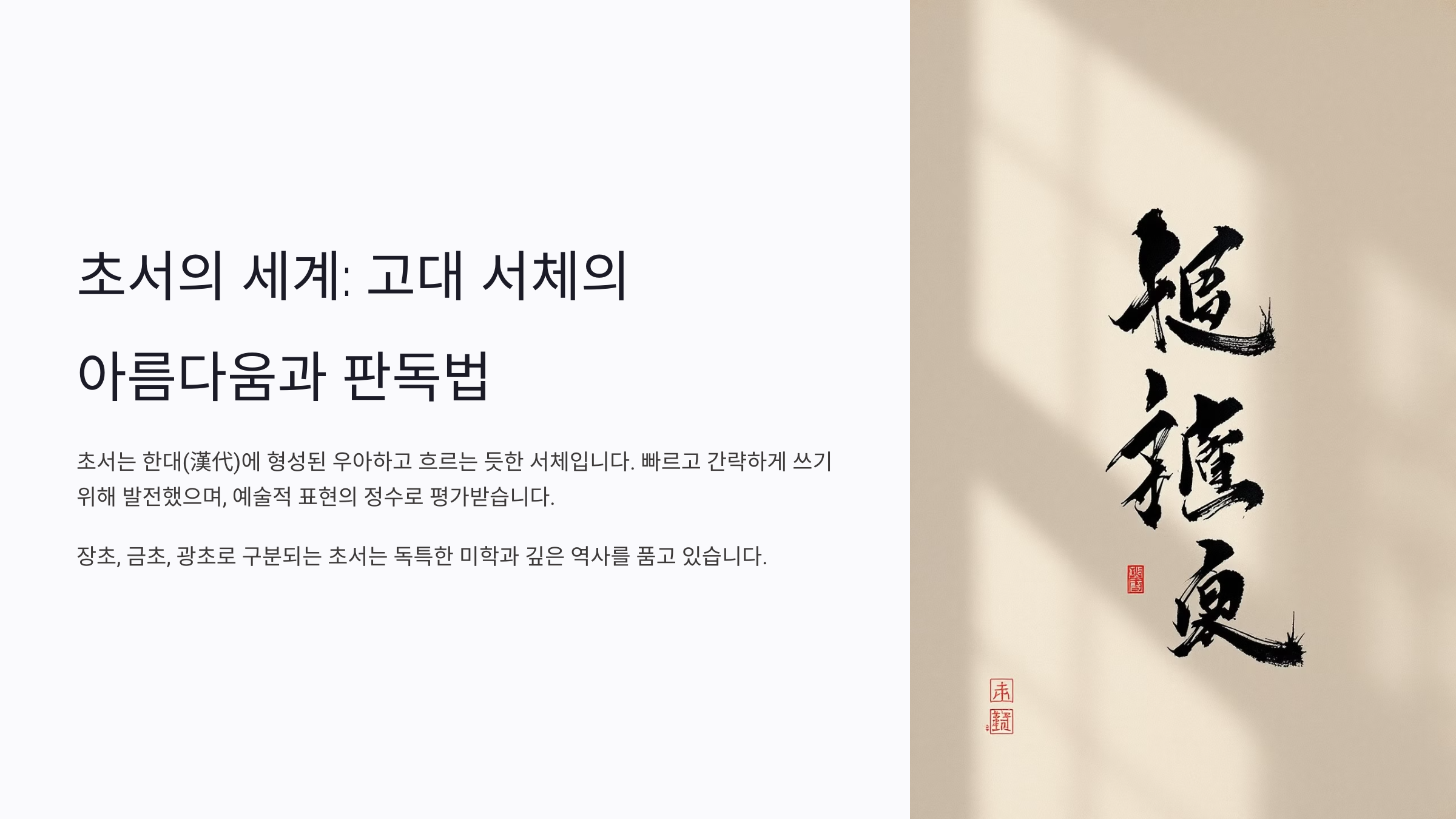
초서는 한자의 필기체로, 한대(漢代)부터 발전하기 시작했어요. 한자의 기존 획을 단순화하고 이어 쓰면서 더욱 빠르게 기록할 수 있도록 만들어졌어요. 당시 관료나 학자들이 문서를 신속하게 작성할 필요가 있었기 때문에 초서가 널리 사용되었죠.
초서는 크게 장초(章草)와 금초(今草), 광초(狂草)로 나뉘어요. 장초는 전서나 예서의 특징이 남아 비교적 읽기 쉬운 편이에요. 반면, 금초와 광초는 획이 더욱 과감하게 생략되고 연결되어 난해한 경우가 많아요.
초서가 가장 발달한 시기는 당대(唐代)로, 손과 팔의 자연스러운 움직임을 강조한 필법이 정립되었어요. 대표적인 초서 대가로는 장욱(張旭), 회소(懷素) 같은 인물들이 있어요.
📝 초서 유형 비교표
초서 유형 특징 난이도 대표 서예가 장초(章草) 예서에 가까운 초서, 상대적으로 쉽게 판독 가능 ★☆☆☆☆ 서승(徐僧), 두우(杜佑) 금초(今草) 획이 연결되고 약간의 생략이 있는 초서 ★★★☆☆ 장욱(張旭), 손과(孫過) 광초(狂草) 획의 생략과 변형이 극대화된 초서 ★★★★★ 회소(懷素), 장욱(張旭) 초서의 유형별 특징을 이해하면 문서의 난이도를 예측하고 판독에 접근하기 쉬워요. 특히 장초부터 시작해 점차 금초, 광초로 넘어가는 연습이 중요해요.
🖋 초서의 기본 구조와 서법
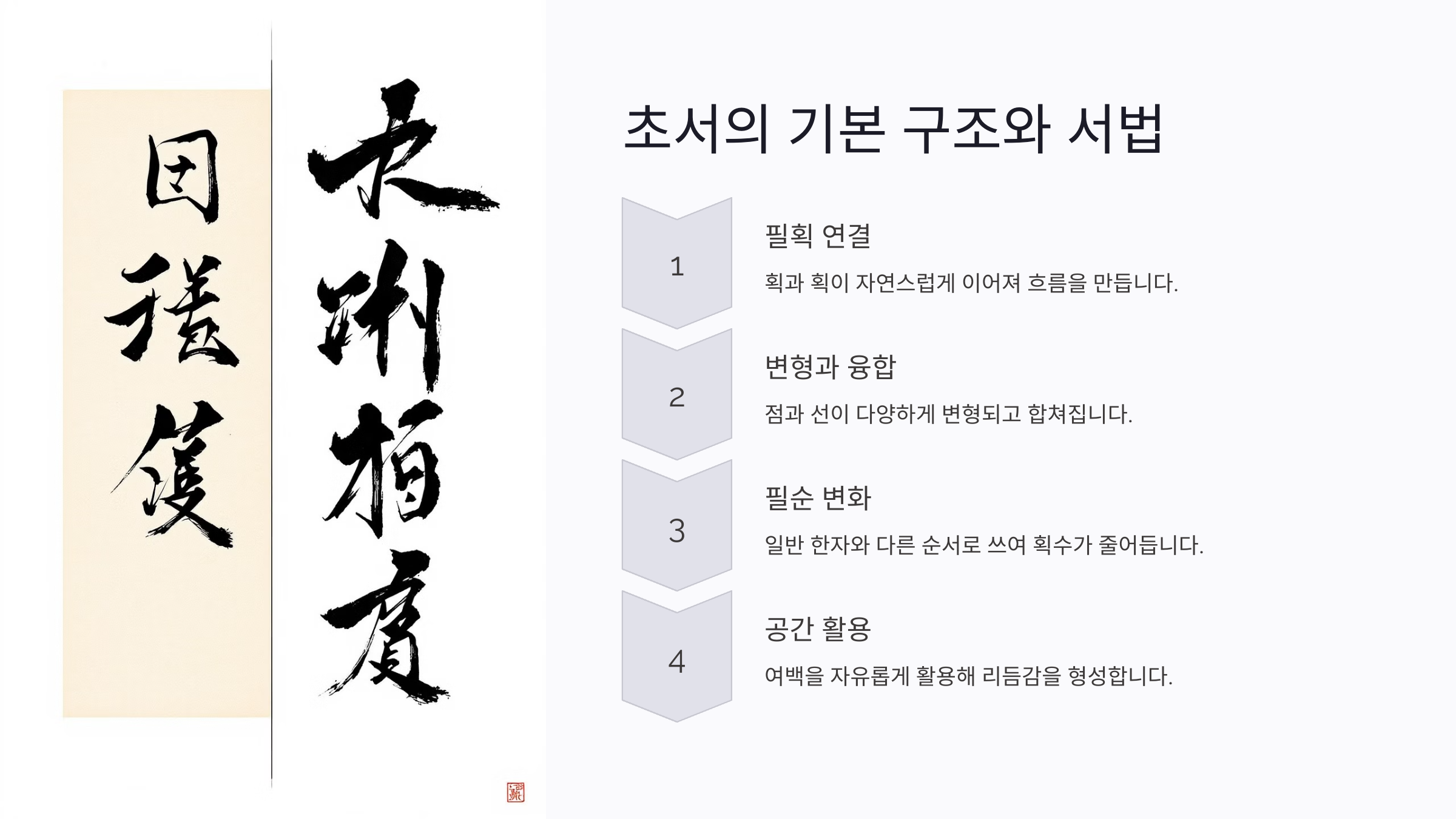
초서는 기본적으로 기존 한자의 획을 간략하게 줄이거나 이어 쓰는 방식으로 구성돼요. 글자의 균형을 유지하면서도 빠른 필기가 가능하도록 변형되었기 때문에 초서를 읽기 위해서는 이러한 변형 원리를 이해하는 것이 중요해요.
초서의 기본 원리는 획 생략(省筆), 획 연결(連筆), 획 변화(變筆)로 나뉘어요. 이를 통해 기존 한자의 형태가 완전히 달라질 수 있어요. 예를 들어, '永(영)'자는 초서에서 단순한 곡선으로 변형될 수 있고, '書(서)'자는 여러 획이 한 붓으로 연결되기도 해요.
초서를 작성할 때 중요한 요소는 ‘서법(書法)’이에요. 초서는 단순히 글씨를 빨리 쓰는 것이 아니라, 특정한 필법과 흐름을 유지하는 것이 핵심이에요. 필획의 방향, 필압, 속도 등에 따라 글자의 분위기가 완전히 달라질 수 있어요.
✍ 초서 변형 원리
변형 원리 설명 예시 획 생략 (省筆) 글자의 일부 획을 생략하여 간결화 書 → 弢 획 연결 (連筆) 여러 획을 한 번에 이어 써서 필기 속도 향상 水 → 氵 획 변화 (變筆) 획의 형태를 변형하여 새로운 글씨체로 발전 馬 → 屮 초서를 판독하려면 이런 변형 패턴을 익혀야 해요. 특히 ‘획 생략’과 ‘획 연결’이 많이 적용된 글자는 난이도가 높기 때문에 초서 대가들의 필적을 참고하는 것도 좋은 방법이에요.
🔍 초서 판독을 위한 핵심 규칙
초서를 정확하게 판독하려면 몇 가지 핵심 규칙을 이해하는 것이 중요해요. 초서의 특징상 획이 연결되거나 생략되는 경우가 많아, 문맥을 고려하며 해석해야 해요. 단순히 글자 하나하나를 읽는 것이 아니라, 문장 전체의 흐름을 파악하는 것이 핵심이에요.
초서를 판독할 때 가장 먼저 해야 할 일은 '획의 패턴'을 파악하는 것이에요. 초서는 필기 속도를 높이기 위해 획을 줄이거나 이어 쓰는 특징이 있기 때문에, 특정 패턴이 반복되는 경우가 많아요. 초서에서 자주 변형되는 글자들을 익히면 판독이 훨씬 쉬워져요.
또한, 필기 습관에 따라 동일한 글자라도 다양한 형태로 나타날 수 있어요. 같은 사람이 쓴 초서라도 상황에 따라 획이 달라질 수 있기 때문에 여러 필체를 비교하며 연습하는 것이 중요해요. 초서 판독의 기본 규칙을 익히면 어떤 문서라도 해석할 수 있는 실력이 길러질 거예요.
📌 초서 판독 핵심 규칙
규칙 설명 예시 문맥 파악 초서는 글자 하나만 보면 어려울 수 있으므로 문맥을 고려해야 함 前後關係(전후관계) 고려 반복되는 패턴 확인 동일한 글자가 다양한 형태로 쓰이는 경우를 익혀야 함 永 → 여러 변형 가능 서체 비교 서예가마다 초서 스타일이 다르므로 여러 필체를 비교 장욱 vs 회소 이 규칙들을 익히면 초서를 판독하는 능력이 향상될 거예요. 특히 자주 등장하는 변형된 글자들을 암기하면 더욱 쉽게 초서를 해독할 수 있답니다.
⚠️ 초서 판독 시 흔히 하는 실수
초서를 판독할 때 많은 사람들이 공통적으로 저지르는 실수가 있어요. 이런 실수를 줄이면 초서 해독 능력을 더욱 빠르게 향상시킬 수 있어요. 특히 초서를 처음 접하는 사람들은 자주 등장하는 오류를 알고 조심하는 것이 중요해요.
가장 흔한 실수 중 하나는 '모든 획을 찾으려는 시도'예요. 초서는 필기체이기 때문에 원래 한자의 획이 일부 생략되거나 연결되기도 해요. 초서를 판독할 때는 원형을 억지로 찾기보다, 글자의 흐름을 이해하고 유추하는 것이 중요해요.
또 다른 실수는 '초서 글자를 한 글자씩 따로 해석'하는 거예요. 초서는 문장 속에서 자연스럽게 연결되므로, 개별 글자보다는 문맥을 고려해야 정확한 의미를 파악할 수 있어요. 한 글자만 보고 의미를 단정 짓지 말고, 앞뒤 문장을 살펴보는 습관을 들이는 것이 좋아요.
🚫 초서 판독 시 흔히 하는 실수
실수 유형 설명 해결 방법 획을 모두 찾으려 함 초서에서는 일부 획이 생략될 수 있음 글자의 전체 형태와 흐름을 파악 문맥을 고려하지 않음 한 글자만 보고 의미를 단정 지음 앞뒤 문장과 연계하여 해석 서체 차이를 고려하지 않음 작가마다 필체가 다름 여러 서예가의 필체를 비교하며 학습 이런 실수를 줄이면 초서를 훨씬 수월하게 읽을 수 있어요. 특히 초서 학습 초반에는 '모든 획을 보려 하지 않기'와 '문맥 속에서 의미를 파악하기'를 꼭 기억해야 해요.
📖 초서 판독 실전 연습 방법
초서 판독 실력을 키우려면 꾸준한 연습이 필수예요. 단순히 초서를 보는 것만으로는 실력이 늘지 않기 때문에, 체계적인 연습 방법을 활용하는 것이 중요해요. 초서 연습은 크게 '기본 글자 학습', '실제 문서 판독', '서예 연습' 세 가지로 나눌 수 있어요.
기본 글자 학습에서는 자주 변형되는 초서 글자들을 반복적으로 익히는 것이 중요해요. 특히 ‘永(영)’이나 ‘書(서)’처럼 기본적인 필법이 녹아 있는 글자부터 시작하는 것이 좋아요. 초서 대가들의 글씨를 보고 직접 써보면서 형태를 익히는 것도 좋은 방법이에요.
실제 문서를 판독하는 연습도 병행해야 해요. 고문서나 서예 작품을 보면서 문맥 속에서 초서를 이해하는 것이 중요해요. 이때, 원본과 함께 해독본이 제공되는 자료를 활용하면 도움이 돼요. 예를 들어, 장욱(張旭)이나 회소(懷素)의 작품을 비교하며 연습하면 초서의 다양한 변형을 익힐 수 있어요.
📝 초서 연습법 정리
연습 방법 설명 추천 자료 기본 글자 익히기 자주 쓰이는 초서 글자 형태를 익힘 초서 자전(草書字典), 永자 연습 고문서 판독 실제 초서로 쓰인 문서를 읽고 해석 장욱, 회소 서법 자료 직접 써보기 초서를 직접 써보며 흐름 익히기 서예 연습본, 붓글씨 교본 이처럼 단계별로 연습하면 초서를 보다 쉽게 판독할 수 있어요. 무엇보다 꾸준히 연습하는 것이 가장 중요해요. 초서는 처음에는 어려울 수 있지만, 익숙해지면 자연스럽게 흐름을 파악할 수 있답니다.
📚 초서 판독에 유용한 자료와 서적
초서 판독 능력을 향상시키기 위해서는 좋은 자료와 서적을 참고하는 것이 중요해요. 초서는 시대별, 서예가별로 다양한 형태로 발전해 왔기 때문에 여러 문헌을 비교하며 학습하는 것이 효과적이에요.
초서를 배우기 위한 서적은 기본적인 초서 자전(字典)부터 유명 서예가들의 작품집까지 다양해요. 특히, 원본과 함께 해독본이 포함된 책을 활용하면 초서를 보다 쉽게 익힐 수 있어요.
또한, 한문 고문서 연구 자료를 참고하는 것도 추천해요. 초서가 실전에서 어떻게 사용되었는지 이해하는 데 도움이 되거든요. 특히, 역사적 문서나 서예 작품을 직접 읽어보는 것이 가장 효과적인 학습 방법이에요.
📖 추천 서적 및 자료
자료명 설명 추천 대상 초서 자전 (草書字典) 초서에서 변형된 한자의 다양한 형태를 모아놓은 사전 초서 입문자 장욱과 회소의 초서 필적 중국 당대의 대표적인 초서 대가들의 필적을 모은 서적 중급 이상 학습자 한문 고문서 해독 입문 한문 고문서를 쉽게 해석할 수 있도록 설명한 책 실전 활용자 서예 연습 교본 초서를 직접 써보면서 익힐 수 있도록 구성된 교재 모든 학습자 이러한 자료들을 활용하면 초서에 대한 이해도를 더욱 높일 수 있어요. 특히 초서 자전은 반드시 하나쯤 가지고 있는 것이 좋아요. 초서를 판독할 때 유용한 참고 자료가 될 수 있거든요.
❓ 초서 판독 관련 FAQ
Q1. 초서가 너무 복잡해 보여서 어디서부터 시작해야 할지 모르겠어요.
A1. 초서는 먼저 기본적인 자주 등장하는 변형 글자부터 익히는 것이 중요해요. 초서 자전(草書字典)이나 '永'자 같은 기초 글자 연습부터 시작하면 조금씩 익숙해질 거예요.
Q2. 초서와 해서, 행서의 차이는 무엇인가요?
A2. 해서(楷書)는 정자체, 행서(行書)는 약간 흘려 쓴 서체, 초서(草書)는 가장 자유로운 필기체예요. 초서는 속도감이 빠르고 획이 연결되는 것이 특징이에요.
Q3. 초서를 배우는 데 얼마나 걸리나요?
A3. 개인의 학습 속도에 따라 다르지만, 기본적인 초서 글자를 익히는 데는 3~6개월 정도 걸려요. 꾸준히 연습하면 점점 더 빠르게 읽고 쓸 수 있게 돼요.
Q7. 초서를 판독하는 데 가장 좋은 자료는 무엇인가요?
A7. 초서 자전(字典), 장욱과 회소의 초서 필적, 한문 고문서 해독 교재 등이 좋아요. 원본과 해독본이 함께 제공되는 책을 활용하면 더욱 효과적이에요.
Q8. 초서를 공부할 때 도움이 되는 온라인 자료가 있을까요?
A8. 네, 중국 서예 박물관 사이트, 국립 도서관 고문서 데이터베이스, 유튜브 서예 강좌 등을 참고하면 도움이 돼요. 직접 서예가들의 필체를 보면서 공부하는 것도 좋은 방법이에요.
초서는 처음에는 어려울 수 있지만, 꾸준히 연습하면 점점 읽기 쉬워져요. 자주 등장하는 초서 글자를 익히고, 원본 문서를 읽어보는 연습을 하면 판독 실력이 빠르게 향상될 거예요. 즐겁게 초서를 공부해 보세요! 😊📜